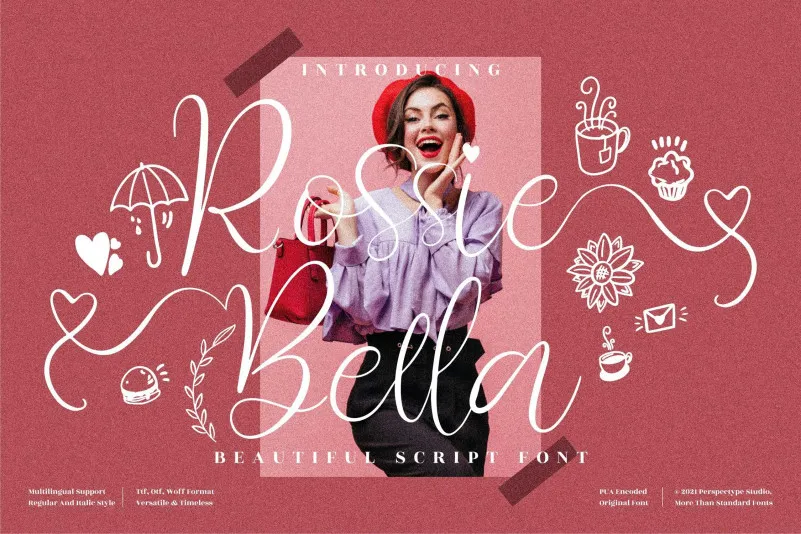
A “Rossie Bella Font” é uma tipografia cáligráfica romântica e delicada com letras que dançam ao redor do nível da linha de base. Suas linhas elegantes e finas conferem um toque sofisticado a qualquer projeto gráfico, tornando-o irresistivelmente luxuoso e sedutor. Com sua forma arredondada e traços finos, essa fonte é perfeita para dar um ar artístico e sofisticado aos textos de marketing, rótulos de produtos ou até mesmo o design gráfico em geral. Seja para criar um infográfico atraente ou apenas adicionar uma pitada única ao seu logo, “Rossie Bella Font” tem tudo o que você precisa para dar vida e emoção às suas criações. Engaje seus leitores com uma tipografia que realmente faz as letras falar, oferecendo uma experiência visual impactante e memorável.